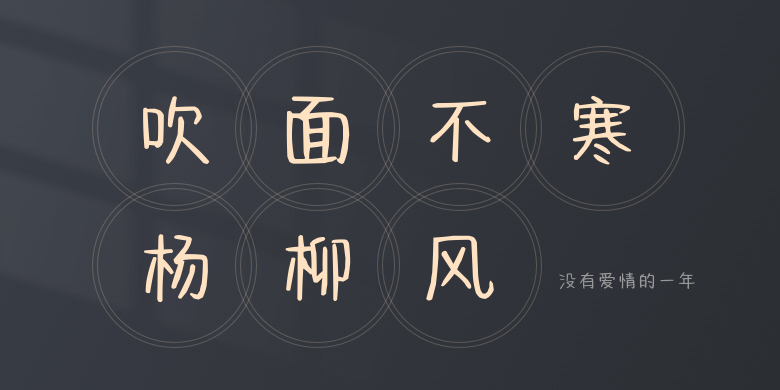
没有爱情的一年
没有爱情的一年,这款字体结构工整、笔画清晰,兼顾美观与易读性,适用于标题、正文、海报、包装、LOGO 等多种场景。字形优雅稳定,风格百搭耐看,适配日常排版与创意设计,让文字呈现更舒适、更具质感。没有爱情的一年一笔一画,皆是细节,以均衡的比例、流畅的线条打造舒适视觉体验,字形端正大气,风格简约现代。无论是商业设计、品牌宣传还是日常排版,都能轻松驾驭,让文字更有格调与力量。没有爱情的一年字体下载。